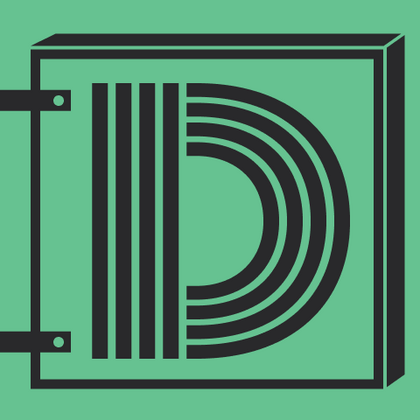
TT Polihaus — экспериментальный гротеск, который на первый взгляд кажется обычным, а затем разбирается на части, превращаясь в трафаретный узор.
Акцидентные шрифты
Акцидентные шрифты образуют целую группу различных по характеру и стилю шрифтов. Несмотря на иногда очень различный внешний вид акцидентных шрифтов, вы легко угадаете их по нескольким признакам:
- крупный размер, часто начинающийся от 14 кегля и выше;
- оригинальный дизайн, который может проявляться как в деталях, например, графике засечек, так и быть авторской задумкой шрифтовых дизайнеров с необычным и узнаваемым стилем.
Эти шрифты предназначены для набора заголовков, использования в рекламных и коммуникационных материалах, таких как баннеры, полиграфическая продукция, брендированная продукция. Могут использоваться для выделения части текста, чтобы усилить акцент на фразе.
Акцидентные шрифты не подходят для набора большого полотна текста, поэтому используются в паре с текстовыми шрифтами. Гарнитуры акцидентных шрифтов имеют более эксцентричный, выразительный дизайн, даже если разрабатываются в дополнение к текстовому шрифту.
Этот вид шрифтов может иметь формальный или неформальный внешний вид, отражать любое настроение и подстраиваться под задачи проекта или бренда, для которых будет использоваться. Многие бренды приобретают персонально разработанную для них акцидентную шрифтовую гарнитуру, выступающую элементом фирменного стиля.
В коллекции акцидентных шрифтовых гарнитур от команды TypeType вы найдёте разнообразные по стилю и настроению шрифты. Каждая гарнитура обладает своими характерными чертами и визуальными особенностями. Самые популярные акцидентные шрифты от TypeType — ТТ Травелс Некст (TT Travels Next), ТТ Рикорди Мармо (TT Ricordi Marmo), ТТ Глобс (TT Globs), ТТ Форс (TT Fors). Среди необычных вы встретите ТТ Гикетт (TT Geekette), ТТ Франтц (TT Frantz), ТТ Милкс (TT Milks).
TT Nooks Serif — акцидентная новостильная антиква с лёгким налётом эгоцентричности. У неё острый и твёрдый, при этом элегантный и статный характер.
TT Nooks Script — шрифт с уникальным рисунком, который не имеет прямых аналогов.
TT Qurdisma — узкий и плотный декоративный шрифт, напоминающий причудливое растение. Вьющиеся, плавные контуры рождают растительный орнамент.
TT Dott — экспериментальный пиксельный гротеск, в котором за основу пикселя взят круг. Это пластичный и необычный акцидентный шрифт, вызывающий ассоциации одновременно с вышивкой и техно-вечеринками.
TT Supermolot Neue — технологичный модульный гротеск с футуристическим настроением и мощным функционалом. Яркость его характера сочетается с универсальностью применения.
TT Runs — это выразительный шрифт, который идеально впишется в проекты со спортивной тематикой. При этом гарнитура отлично подойдет и для других современных проектов: после обновления сфера ее применения значительно расширилась.
TT Regins — шотландская новостильная антиква с королевским характером. Яркий контраст и острые треугольные засечки придают этому шрифту строгий и властный нрав.
В TT Frantz можно найти небольшие отсылки в эстетике арт-деко, которые выражены в сильно заниженной или наоборот сильно завышенной талии у букв. Кроме того, в зависимости от положения ползунка регулировки оси, у некоторых букв изменяется закрытость апертуры.
TT Quaris — изысканная и современная ленточная антиква. Перед разработкой этой гарнитуры мы провели глубокое исследование архетипов ленточных антикв.
TT Ricordi Allegria — современная ленточная антиква, отличительные особенности которой, гиперболизированная разноширинность в пропорциях, контраст между штрихами, клиновидные окончания штрихов и отсутствие традиционных засечек.
TT Bakers — пластичная антиква с нежным и живым характером. Этот шрифт похож на свежую выпечку: он тёплый и мягкий, особенно в жирных начертаниях.
TT Norms® Pro — один из самых востребованных шрифтов студии, выбор известных мировых брендов. Более трёх переизданий за семь лет, первые строчки на MyFonts, десятки кастомизаций. Это «рабочая лошадка», которая станет незаменимой базой любой шрифтовой коллекции.
TT Commons™ Pro — один из самых востребованных шрифтов студии. Сфера его применения практически безгранична! Беспроигрышный вариант для тех, кто ищет стильный и функциональный базовый шрифт для любых проектов.
TT Hoves Pro — скандинавский гротеск с нейтральным, но в то же время узнаваемым характером. Это удобный и функциональный, при этом стильный и эстетичный инструмент для дизайнеров. Такой шрифт позволит вам решать множество разноплановых задач!
TT Supermolot Neue — непобедимое оружие в борьбе за стиль! Это технологичный модульный гротеск с футуристическим настроением и мощным функционалом. Шрифт идеально подойдёт для оформления компьютерных игр и множества других проектов.
TT Paplane — акцидентный сквадраченный гротеск. Так, характерные черты этого гротеска — сквадраченные формы, 45-градусные срезы и обтекаемые внешние контуры.
TT Cometus — современная брусковая антиква. Название гарнитуры отсылает к образу кометы — мощного увесистого тела с красивым хвостом, грациозно рассекающего космические просторы с огромной скоростью.